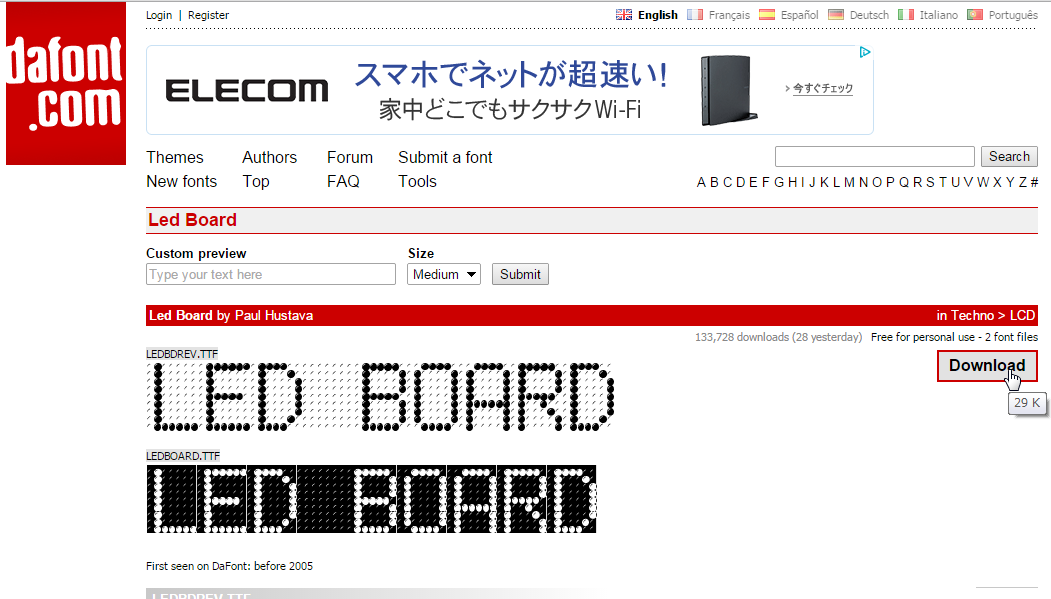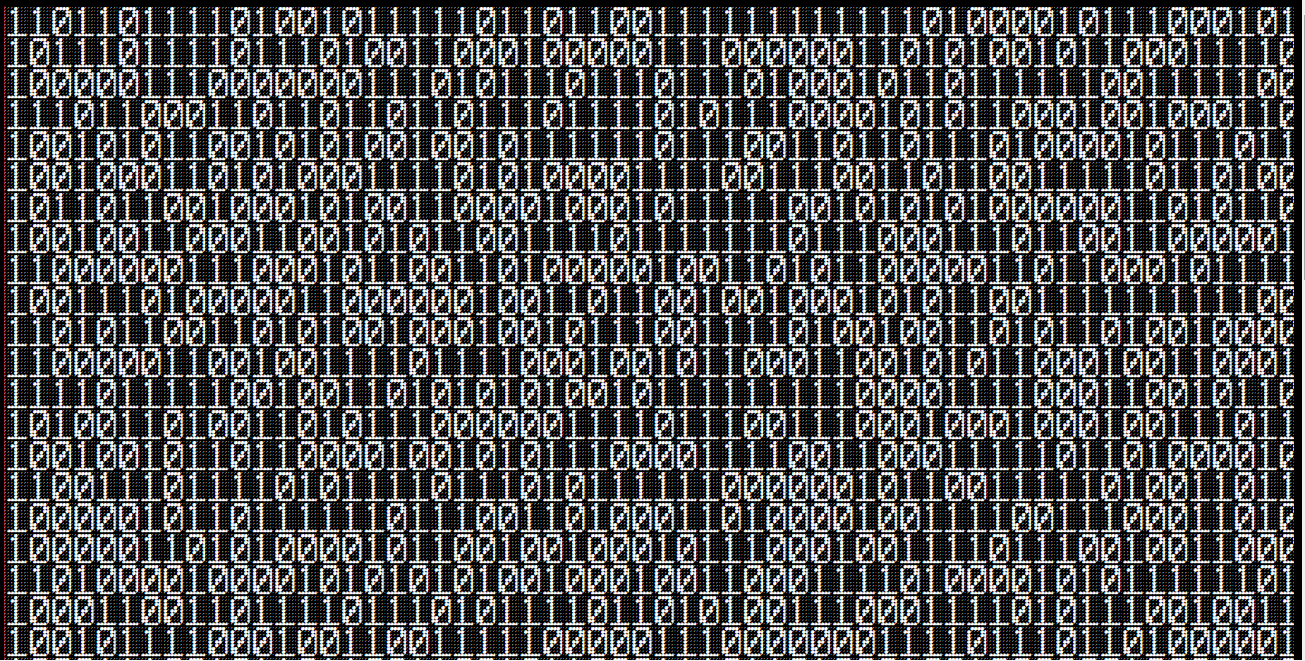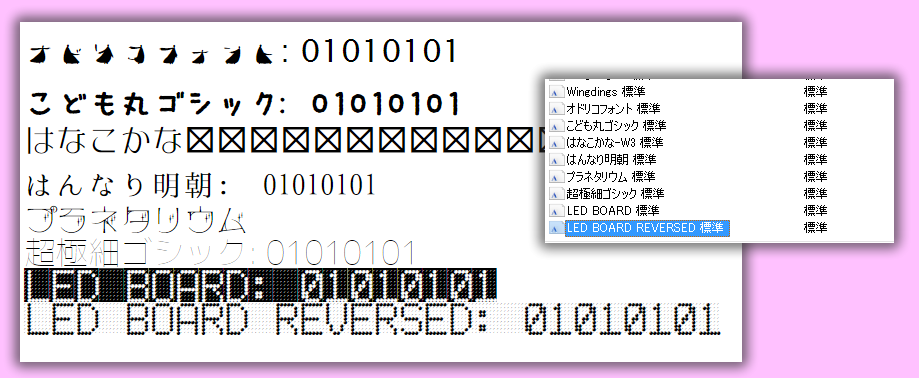
Webサイトを作るときにどのフォントで表示するか、というのは大体定番が決まっていて、あまり新しいフォントを指定することはありません。というのもWebを見てもらう場合に使われるフォントはユーザーのPCに入っているフォントが利用されるので一般的なフォントを使うことがほとんどだからです。
しかし、ちょっと変わったフォントでローカルのWebを作って表示して、blogの画像にしてみようかしら?と思ってよく使うフォントで無いものをダウンロードしてきたのですが。はて、どうやってフォント指定するのかな?と思って調べたのでそれについて書きます。
こんな事がしたかったのです
フリー素材で 01010101 みたいな表示をさせたモノが斜めから写真で撮影されたモノ。。わ、わかりにくいですね。えーと、
これを見つけました。このまま使おうかなーと思ったのですがもちょっと横幅が欲しいとか思ったりしました。他のサイトにも似たようなモノがないか探したんですがちょっとみつからなくて。
あーでもこれ0と1ならPHPかなんかで表示して、フォントも「それっぽい」感じのを探してきて自分で表示すれば好きなように撮影できるんじゃない?と思ったのです。
電光掲示板風の数字が表示出来るフォントを探す
このちょっと電光掲示板風のフォント、とりあえず自分のPCに入っているフォントを見てみましたがありません。ということで
電光掲示板風 フォント
で探して、この一覧から
LED BOARD というフォントを見つけました。
パソコンに入っているフォントをfont-familyで指定する
色々試行錯誤して分かった結果を書きますが、C:\Windows\Fonts でフォントを見たときの名前(標準や太字などと書いてある部分以外) をそのまま font-family に書けばそのフォントでブラウザに表示されます。ただし、もちろん変わったフォントなど全ての人のPCに入っている訳では無いので変わったフォントで必ず表示されるのは自分のPCだからなのですが。
Fontsにこんな感じで表示されています。この オドリコフォント から さきほどダウンロードして持って来たフォントまでを指定して表示してみます。
こんな感じのPHPを書いて保存して実行すると、
このように各フォントでフォント名と 01010101 という数字が表示されました。
インターネットで皆さんに見ていただくのは無理だと思いますが、htmlで資料を作って印刷したりpdfにしたりするには便利かもしれません(^^)。
面倒なのは名前を見たまま入力しなければいけないことで、右クリックしてプロパティではこの名前をコピーできるところがみつかりませんでした。
この名前(拡張子部分をはずしたもの)で指定すると日本語フォントはOKだったのですが、英語フォントはこの名前で指定してもフォントが変更できませんでした。
たぶんプログラムを書けばこの表示されている フォントの名前 を取ってくることができると思うのですが、そこまでしなくてもまぁいいかなぁ(^_^;と思ってとりあえず自分のやりたい 01010101 で画像を作るということに挑戦してみました。
01010101で表示されるPHPを書いてみた
ということでフォントは黒バックの LED BOARD を使って、PHPを書いてみました。
内容は50行繰り返しを行ってその中で mt_rand() で乱数を発生させたモノを decbin で二進数に(0か1)変換したモノを表示を10回繰り返す というかんじです。
ローカルで実行すると、
こんな感じに表示されました。F11キーで全画面表示にして、iPhoneのカメラで撮影したのがこちら、
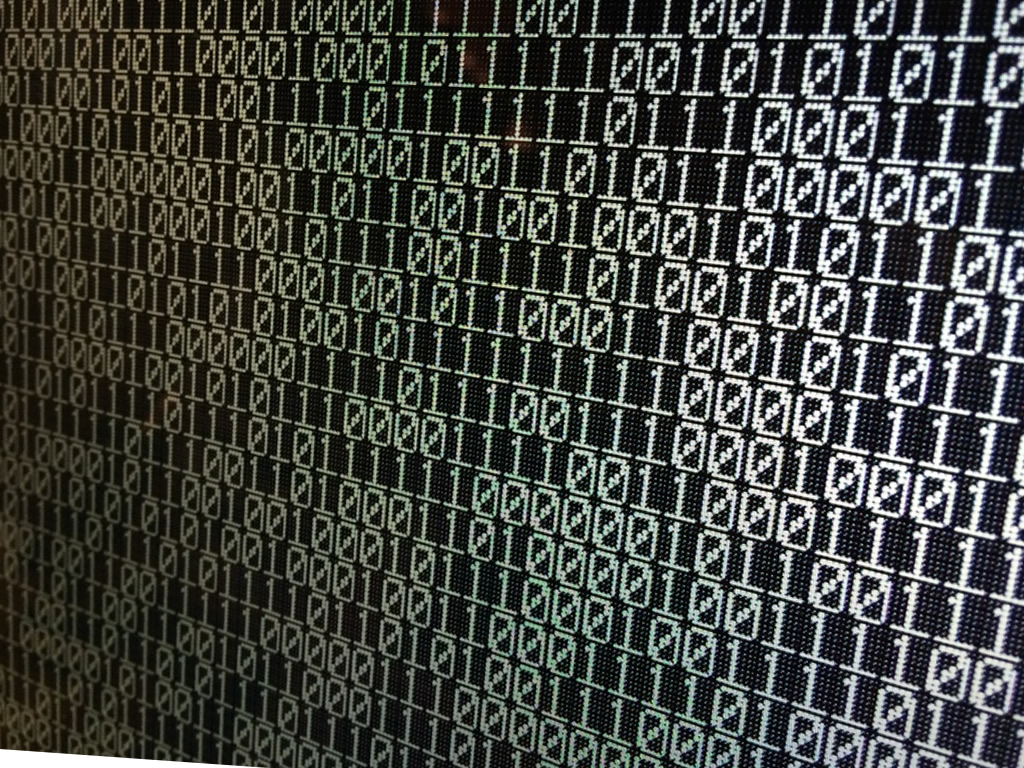
まぁまぁかなぁ(^_^;。あー、今回はとりあえず font-familyの指定の仕方がはっきり分かったというだけでもよしとしたいと思います。